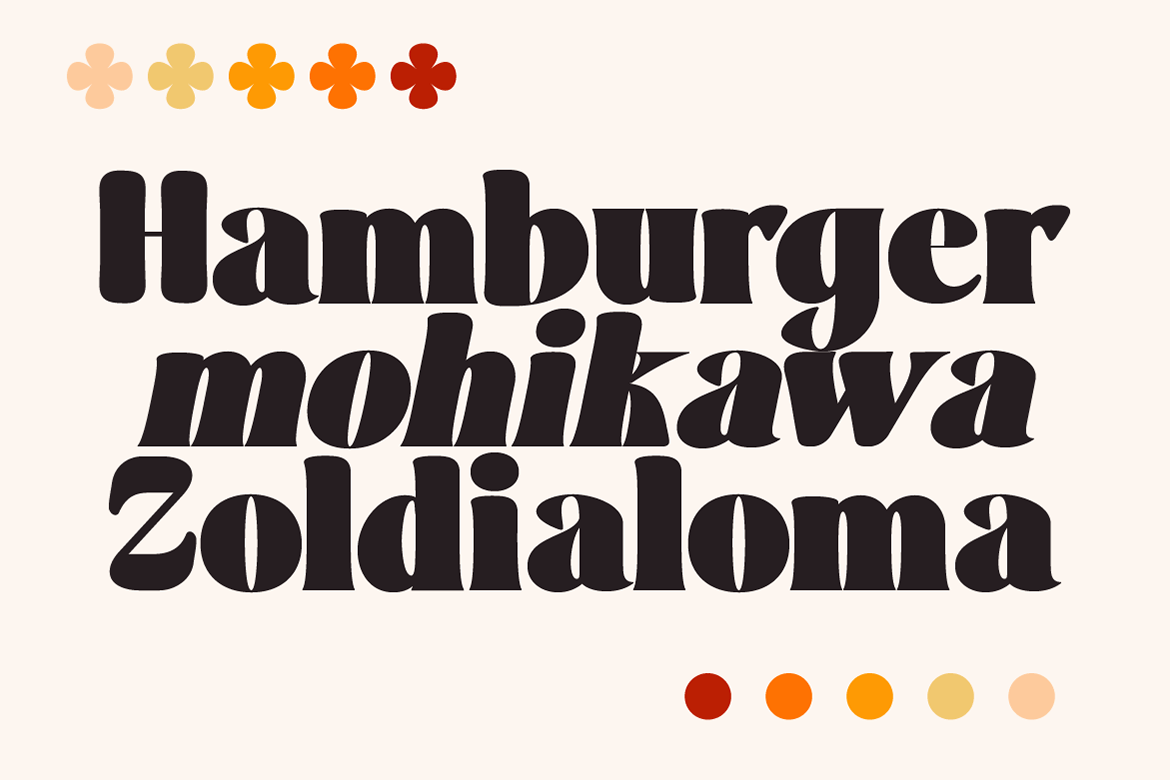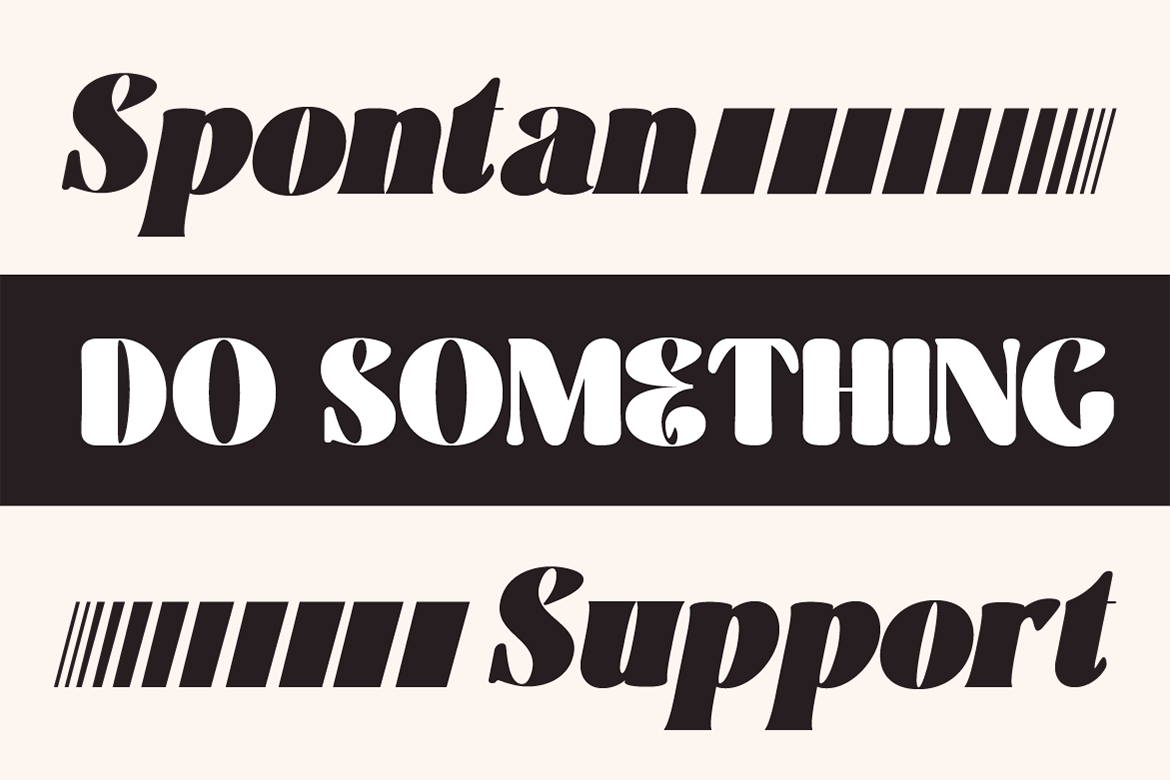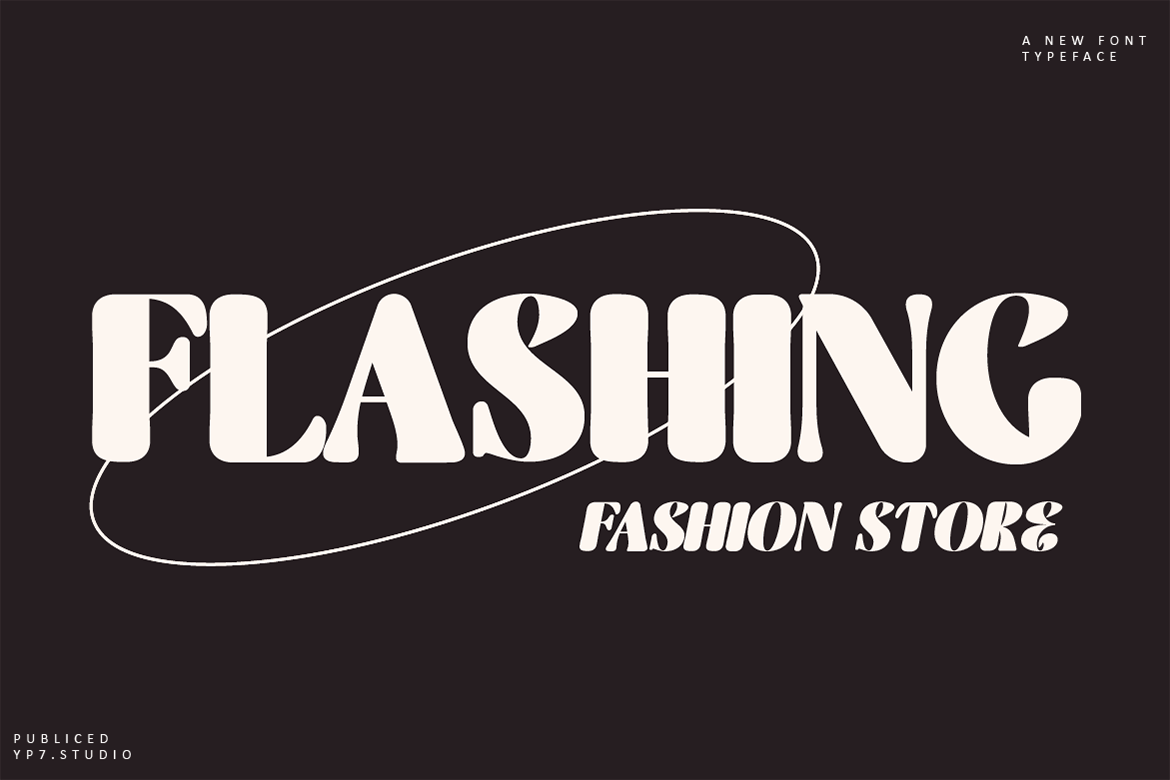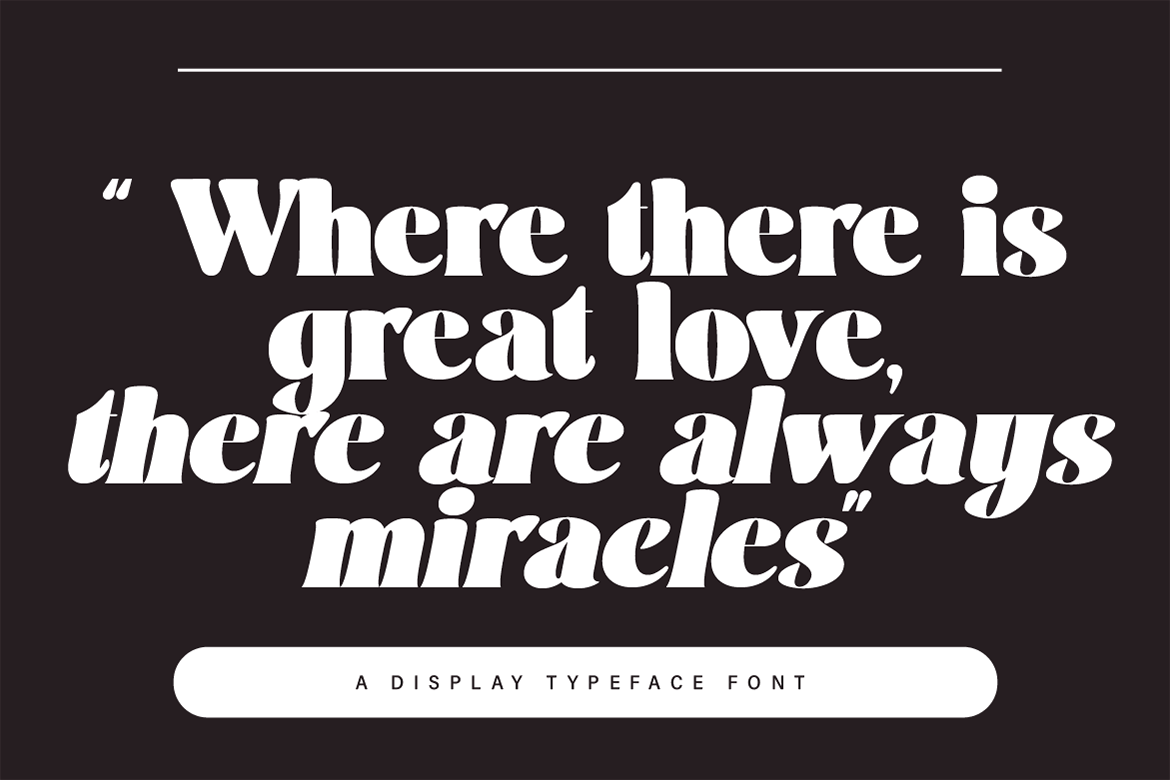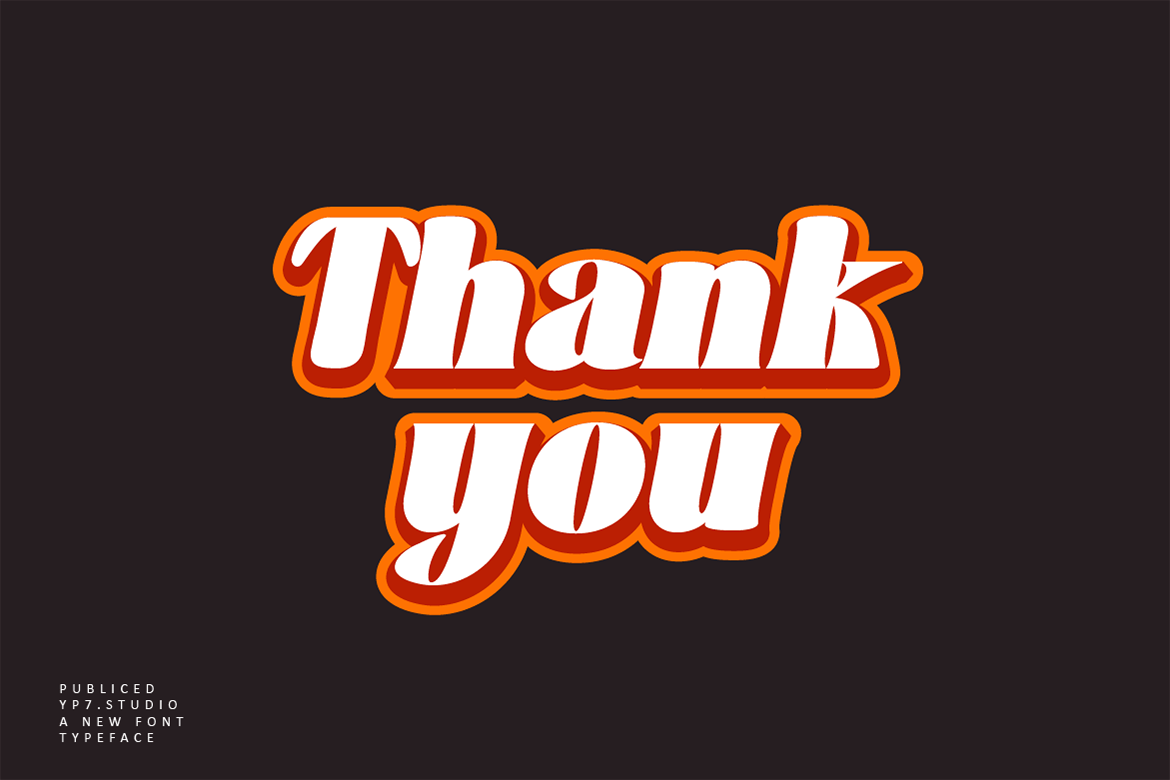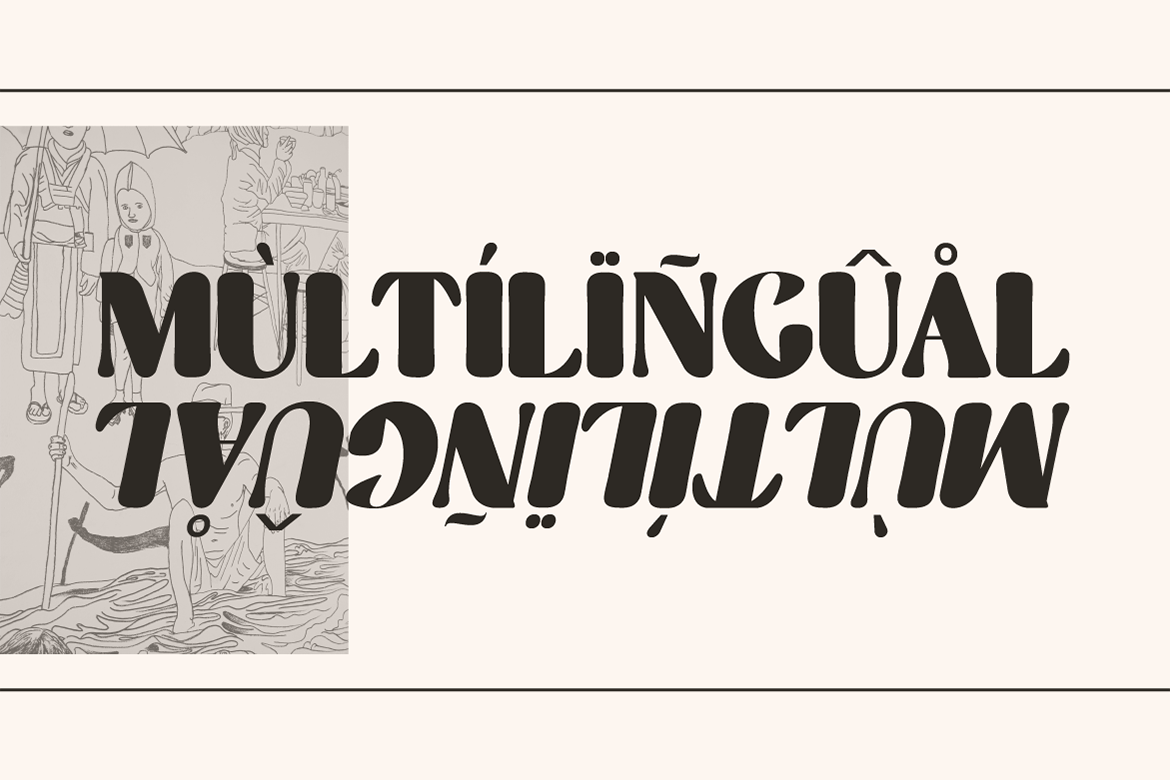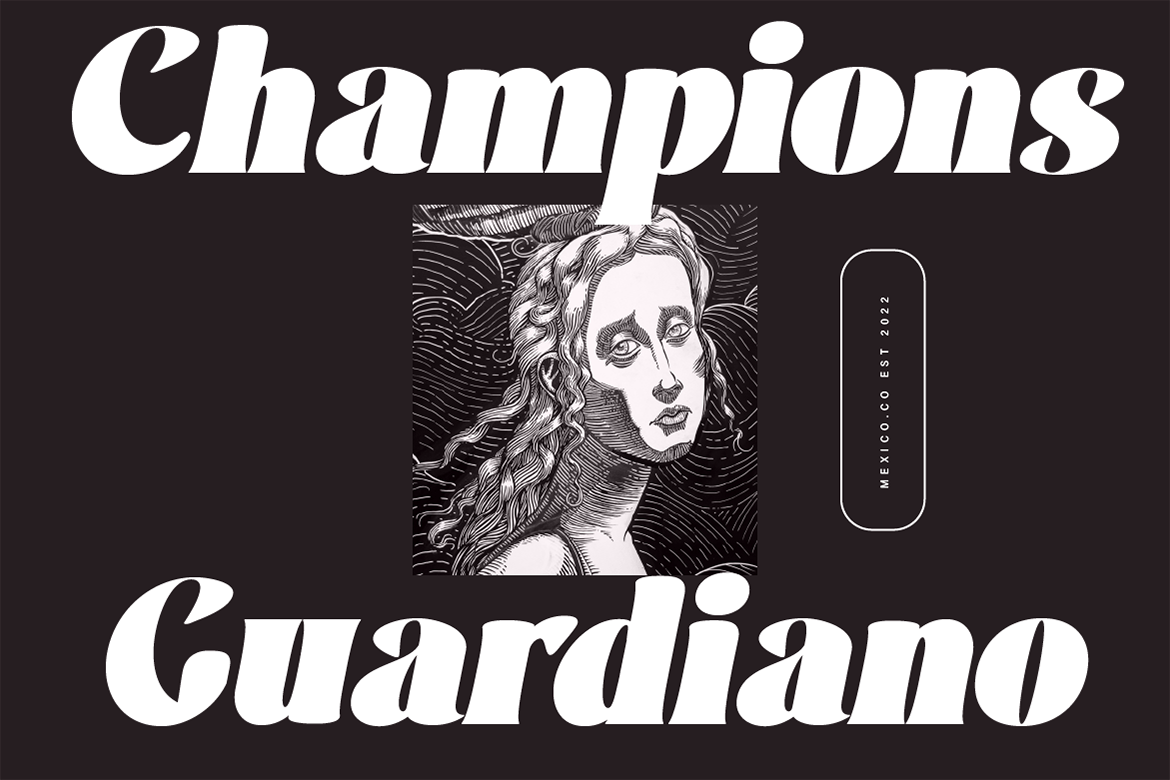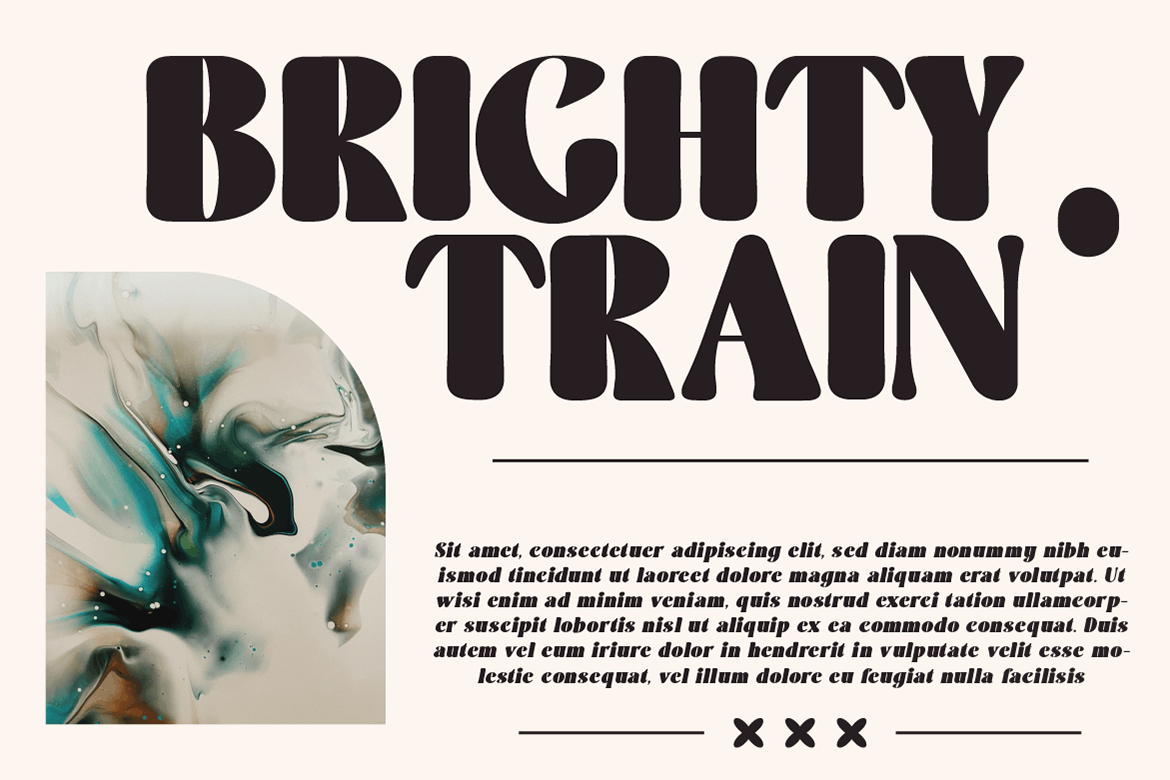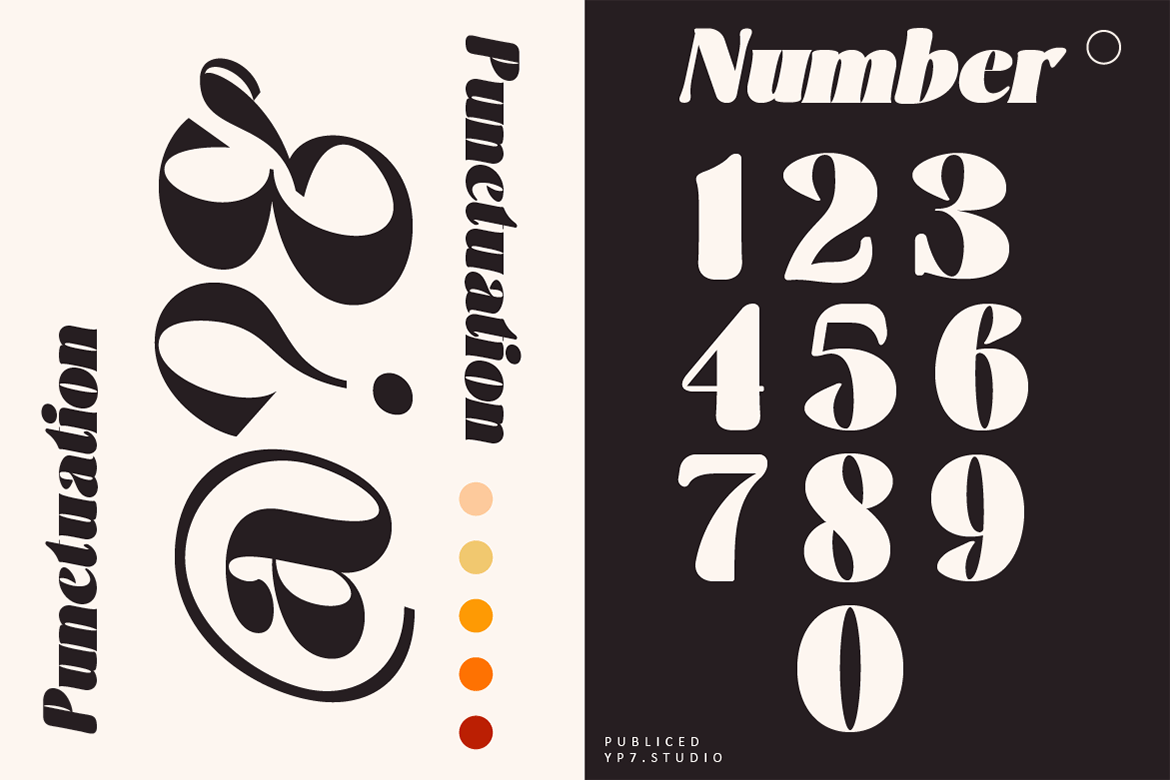
دانلود فونت نمایشی مدرن ریترو Michella Melquin
Modern Retro Display Font
فونت مدرن و ریترو Michella Melquin را دانلود کنید و پروژه‌های طراحی خود را جذاب‌تر کنید.
فونت نمایشی مدرن ریترو Michella Melquin یک انتخاب عالی برای طراحان گرافیک است که به دنبال ایجاد آثار جذاب و خاص هستند. این فونت با طراحی منحصر به فرد خود، می‌تواند به پروژه‌های شما زندگی ببخشد.
• حروف بزرگ
• حروف کوچک
• اعداد و نشانه‌گذاری